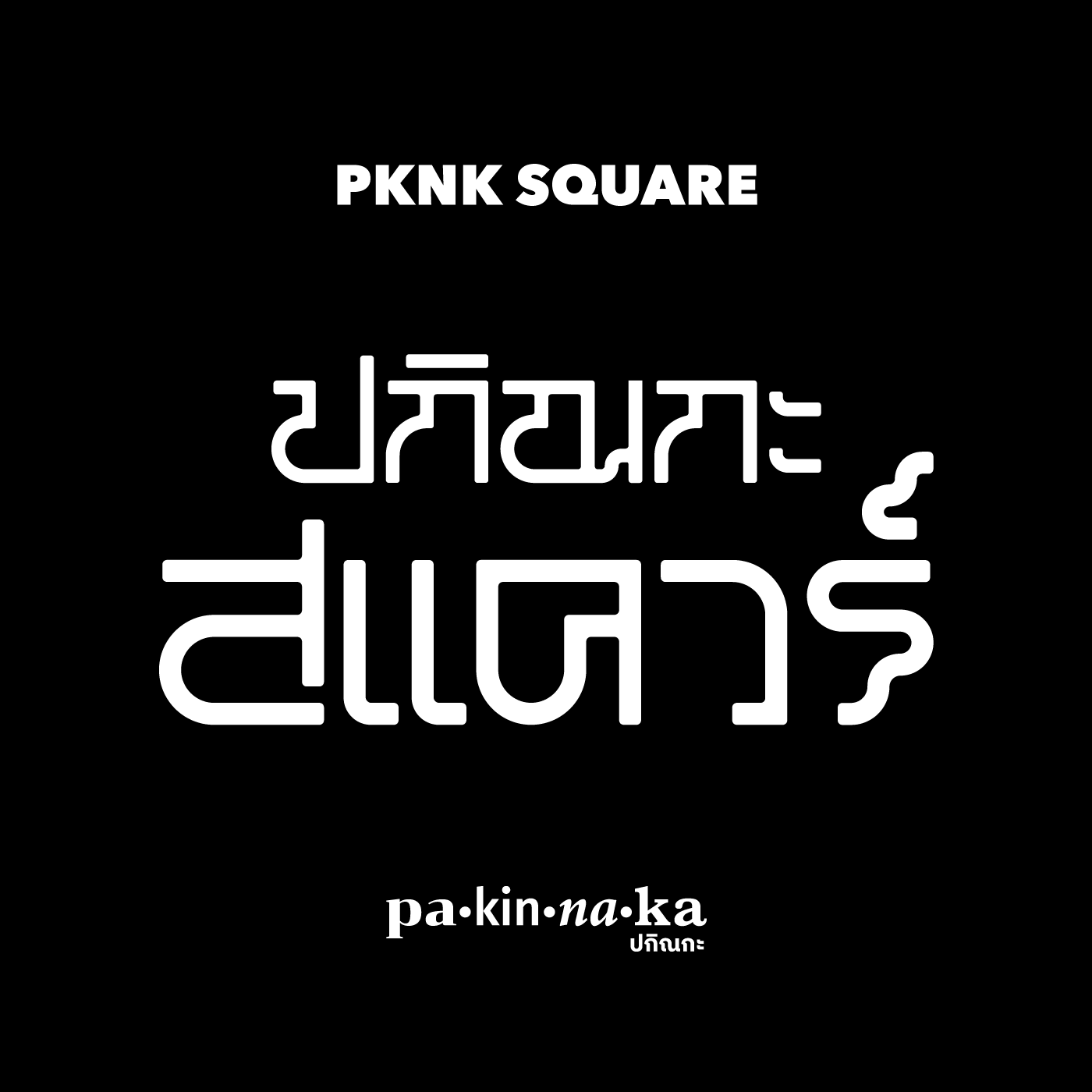
ฟอนต์ "ปกิณกะ แสควร์ / PKNK Square"
ขื่อฟอนต์ : ปกิณกะ แสควร์ / PKNK Square
ออกแบบโดย : Wann R. (จะอ่านว่า "วัน" หรือ "วรรณ" ก็ได้ครับ~)
ฟอนต์ PKNK Square (ปกิณกะ แสควร์) เหมาะกับประโยคสั้นๆ หน้าตายืกยือแบบนี้ประโยคยาวๆ ต้องมีเปลี่ยนอะไหล่ตับแน่นอน~